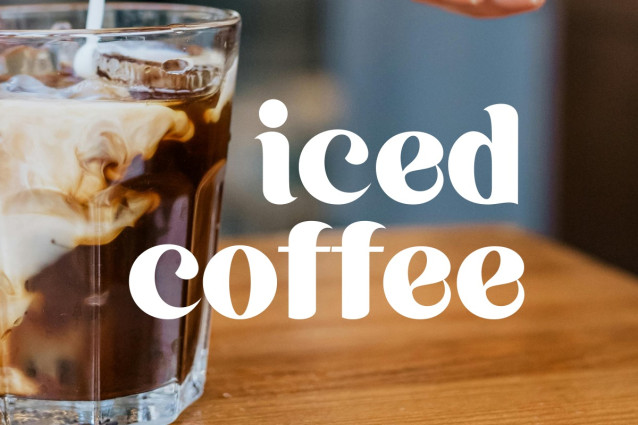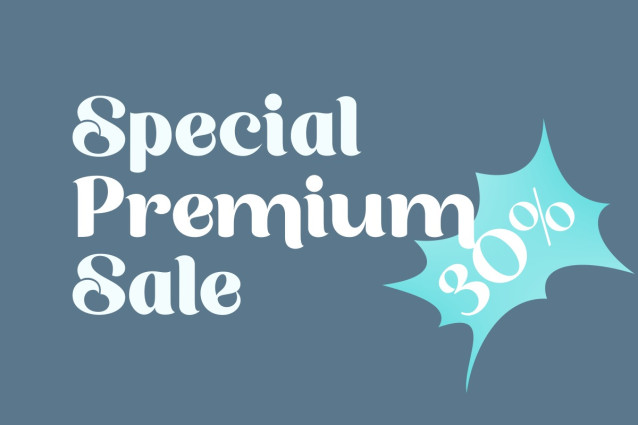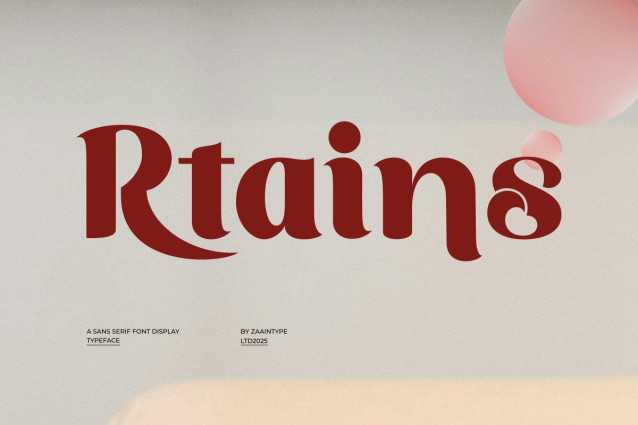
Rtains Font
Rtains font sans serif minimalis dengan karakter yang bersih dan percaya diri. Hadir dalam dua gaya — Regular dan Oblique — Rtains dirancang untuk tampilan yang solid namun fleksibel, ideal untuk kebutuhan branding modern, editorial, dan antarmuka digital.